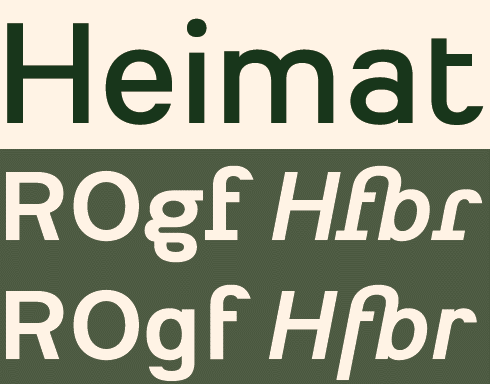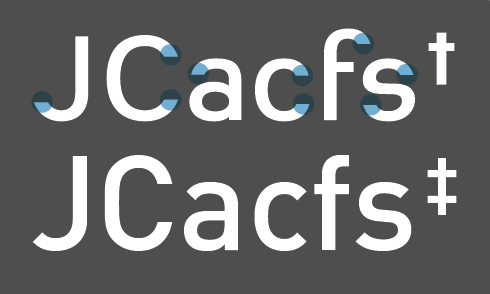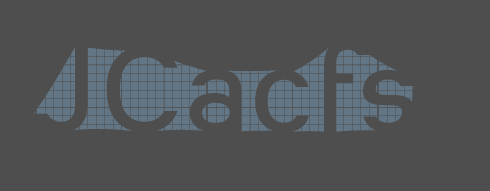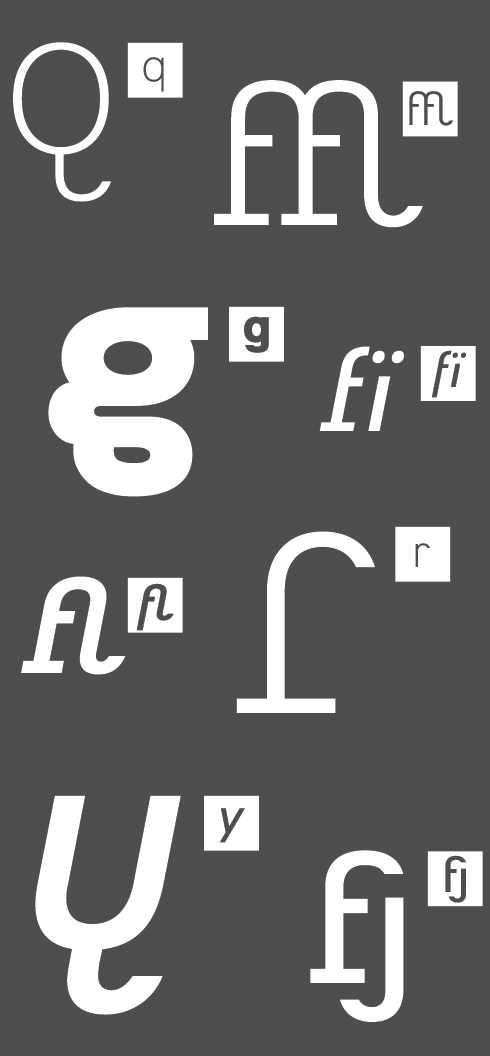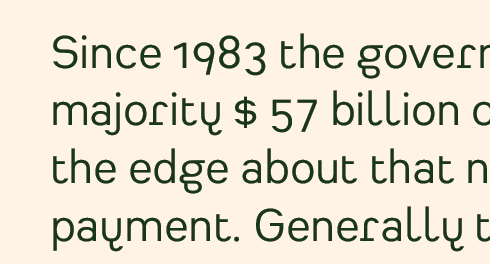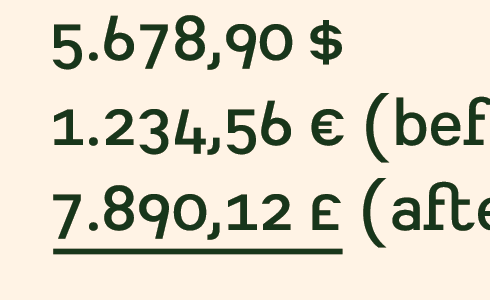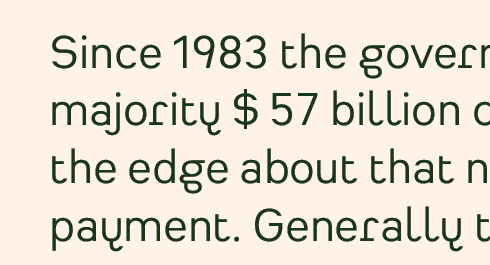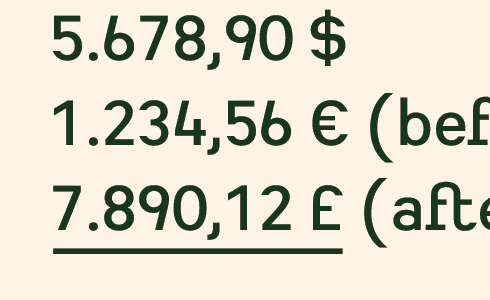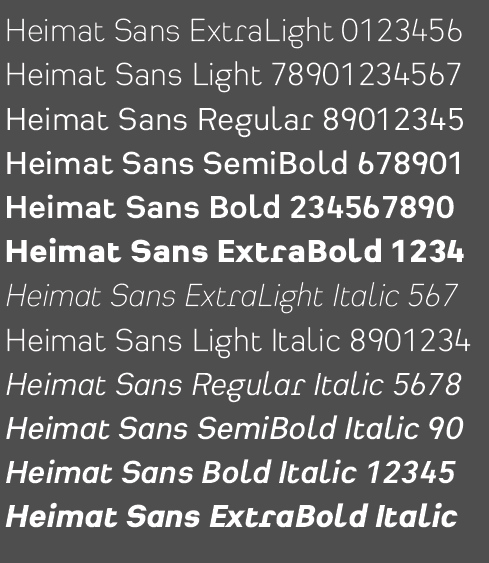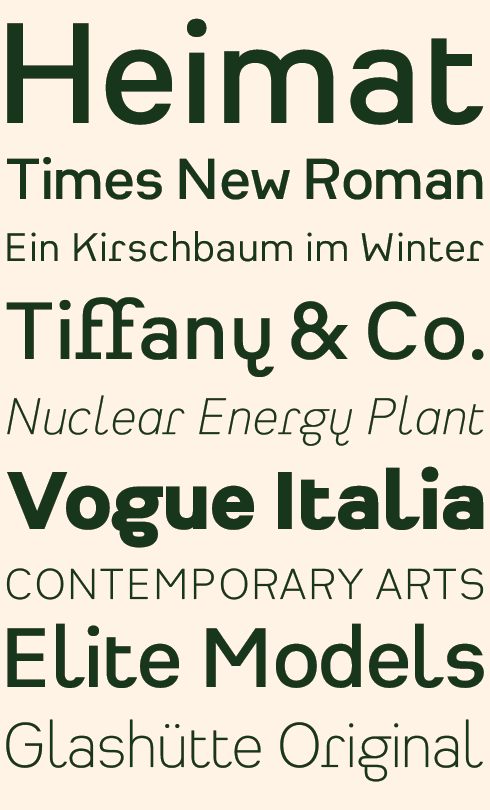
Zwei Schriften in einer Familie
Neutralität und Ausdrucksstärke sind auf den ersten Blick zwei Attribute, die sich ausschließen. Umso interessanter war es eine Schrift zu gestalten, die mit Hilfe von Alternativbuchstaben zwischen beiden Polen oszilliert – eine extreme und zugleich neutrale Schrift sein will. Christoph Dunst hat diese Herausforderung angenommen und legt nun sein neustes Werk vor, die Schriftfamilie Heimat (fontshop.de-Link …).
Der Begriff Neutralität ist nicht unbedingt mit Vertrautheit gleichzusetzen. Viele Schriftkenner halten beispielsweise Akzidenz Grotesk oder Helvetica für neutral, übersehen aber, dass in den Konstruktionen beider Schriften sehr viel mehr Raffinesse steckt, als dass sich die Formen selber erklären. Was diese Schriften neutral wirken lässt ist allein ihre Allgegenwärtigkeit und dass sie deshalb kaum wahrgenommen werden.
Anders verhält es sich mit der DIN-Schrift, die sich aufgrund ihres pragmatischen Aufbaus weniger ästhetischen Kompromissen beugen musste. Hier beginnt die Entstehung der Heimat. »Seit den Arbeiten an der FF-DIN-Familie, die ich für Albert-Jan Pool bereits 2002 begann, habe ich mir oft Gedanken zu der konzeptionellen Gestaltung von konstruierten Groteskschriften gemacht. Ich wollte eine Serifenlose gestalten, deren Formen alle logisch nachzuvollziehen sind, die einen sehr eigenwilligen Charakter hat ohne über eine ›Persönlichkeit‹ zu verfügen.« erinnert sich Christoph Dunst an die ersten Konzepte für Heimat.
Wichtig war ihm, einen geometrischen Gesamteindruck zu erzeugen, ohne die Buchstaben mit einem Baukastenprinzip zusammenzusetzen, wie dies bei DIN beispielsweise der Fall ist. Allerdings sollte die Schrift nicht zu sehr in Richtung Futura gehen, bei der ein O kreisrund aussieht. Somit konnte weniger mit einem Raster gearbeitet werden, als vielmehr mit einem ideellen Konzept, das auf alle Zeichen zu übertragen war.
Die DIN-Schrift basiert auf einem relativ einfachen Gestaltungsprinzip von geraden Elementen und Kurven. Sieht man sich die Versalien der Helvetica an, erkennt man, dass es sich in erster Linie um geschlossene Formen handelt. Bei der DIN gibt es sowohl geschlossene wie offene Endungen. Dass die Kleinbuchstaben allesamt offen sind, wirkt sich gut auf die Lesbarkeit aus.
»Da Heimat über wenige ästhetische Modifikationen verfügen sollte und möglichst streng umgesetzt werden sollte, entschied ich mich, alle runden Endungen geschlossen enden zu lassen.« beschreibt Dunst eines der Heimat-Konstruktionsprinzipien. Der positive Effekt guter Lesbarkeit von offenen Formen sollte jedoch Maßstab sein, was sich schwer mit geschlossenen Formen erzielen lässt: Wer einmal ein Buch in Helvetica lesen musste, weiß was gemeint ist. »Nach umfangreichen Studien entschied ich mich dafür, die Kurven möglichst flach enden zu lassen, so dass der negative Raum die einzelnen Buchstaben im Satz harmonisch verbindet und somit die Lesbarkeit unterstützt:
Des weiteren lag es nahe, den Zeichensatz um Alternativzeichen zu erweitern, damit es eine extreme Variante und eine neutrale gibt. Der Grund weshalb bei dieser Schrift die neutraleren Zeichen als Alternate-Belegung und nicht im regulären Zeichensatz sind, ist ganz einfach die stärkere Charakteristik:
Hanging Figures mit proportionaler Breite für den Einsatz im Text:
Hanging Figures Monospaced für Tabellensatz:
Lining Figures mit proportionaler Breite für den Einsatz im Text und in Headlines:
Lining Figures Monospaced für Tabellensatz:
Heimat ist eine Großfamilie. Der umfangreiche Zeichensatz bietet die Schnitte ExtraLight, ExtraLight Italic, Light, Light Italic, Regular, Regular Italic, Semibold, Semibold Italic, Bold, Bold Italic, Extrabold, Extrabold Italic und ist aufgrund der vielen Ligaturen und alternativen Glyphen nur im OpenType Format erhältlich:
Wer eine frische, gut ausgebaute und vielseitig einsetzbare Schrift sucht, wird mit Heimat große Freude haben. Sie hat sowohl enorme Displaywirkung als auch eine gute Textqualität und lässt sich somit zum Beispiel für Plakate, Leitsysteme und Editorial Design ausgezeichnet einsetzen. Auf den ersten Blick scheint sie durch ihre Eigenwilligkeit die erste Wahl für kulturelle Institutionen und Themen, doch warum sollte ein selbstbewusstes Unternehmen oder eine Marke nicht mit Heimat ihren Anspruch betonen?
Während der Entwicklung von Heimat gab es viele Diskussionen mit Schriftgestaltern, wie streng eine Schrift sein darf und wann die Lesbarkeit wichtiger ist, als die konsequente Umsetzung eines formalen Konzepts. »Für mich stand an oberster Stelle, eine Schrift zu gestalten, der einer interessanten Ausgangsidee zu Grunde liegt, die aber nicht weich gekocht wird um am Ende als witzloser Kompromiss dazustehen. Mein Ziel war, eine Displayschrift mit guter Lesbarkeit zu gestalten. Dass sich Heimat auch in kleinen Größen erstaunlich gut lesen lässt, hatte ich erwartet … und es war trotzdem eine positive Überraschung.« Resümiert Christoph Dunst.
Heimat ist keine Schrift für vorsichtige Gestalter, sondern ein Ansporn, typografisch mehr zu wagen.
Wow, da läuft einem wirklich das Wasser im Mund zusammen. Leider ist der Preis ziemlich hoch für eine Typo, die man nur sehr begrenzt einsetzen kann. Immerhin ist sie aber ein absolutes Unikat.
Eine sehr schöne Schrift, jedoch kippen mir die 6 und die 9 zu doll als wenn diese gleich umfallen würden.
Ich find die Schrift sehr elegant. Lediglich der fette schnitt macht das ganze wieder unheimlich breit aber sonst find ich sie sehr schön.